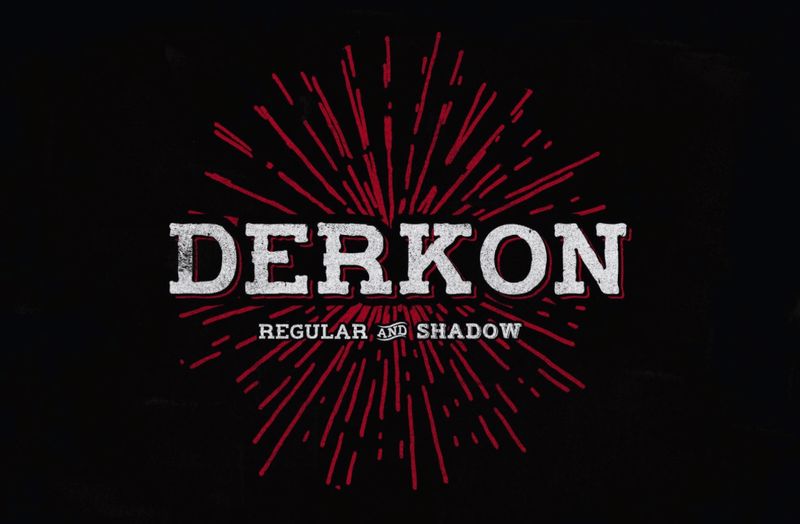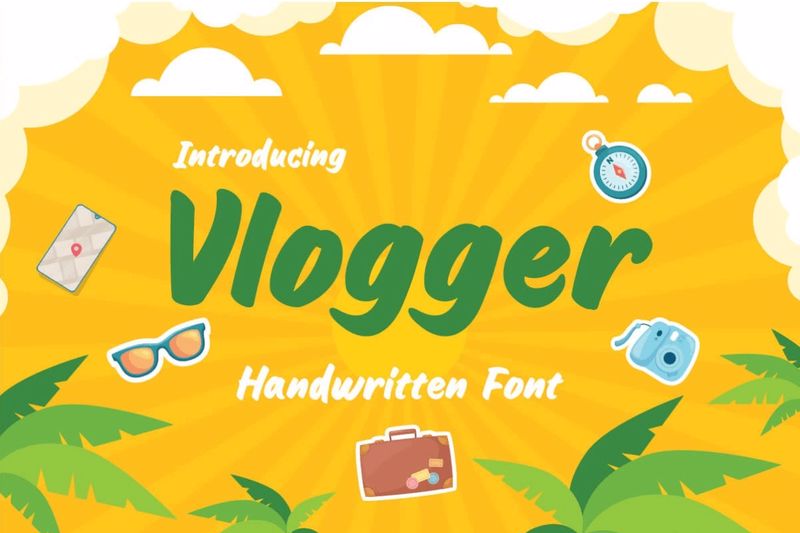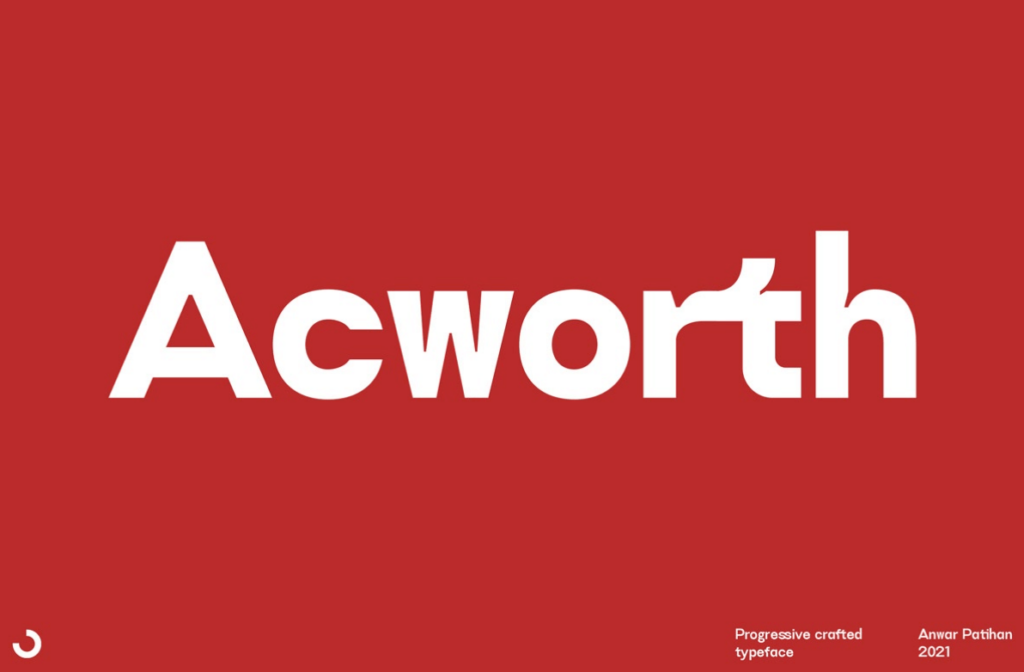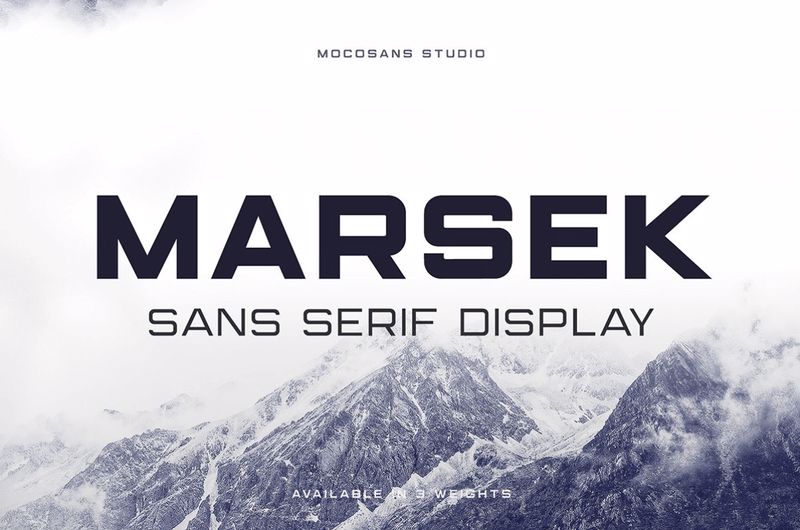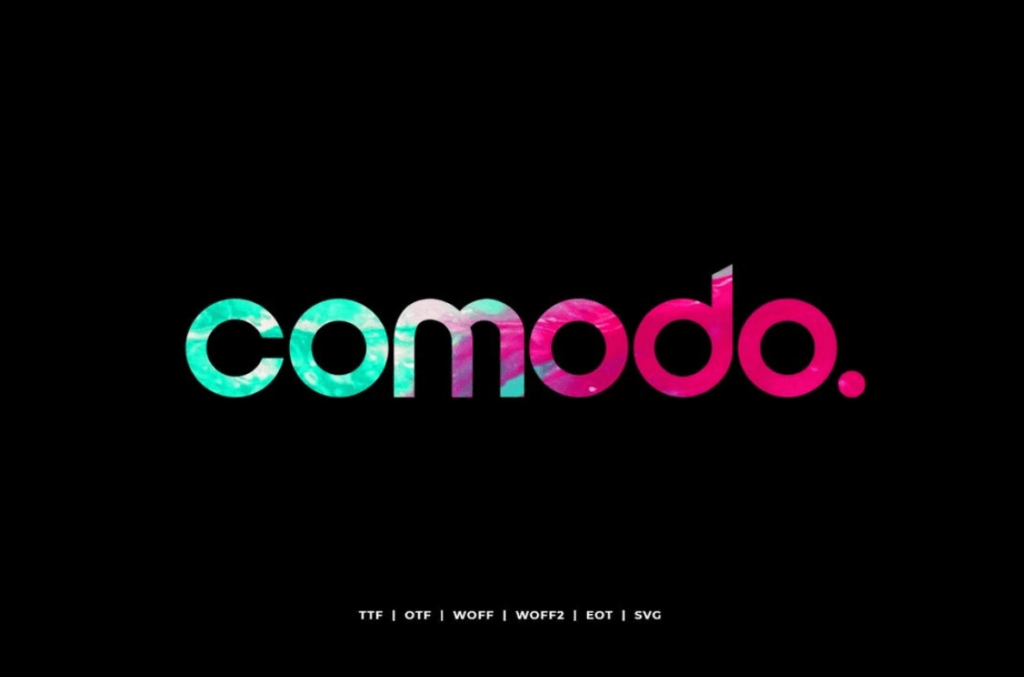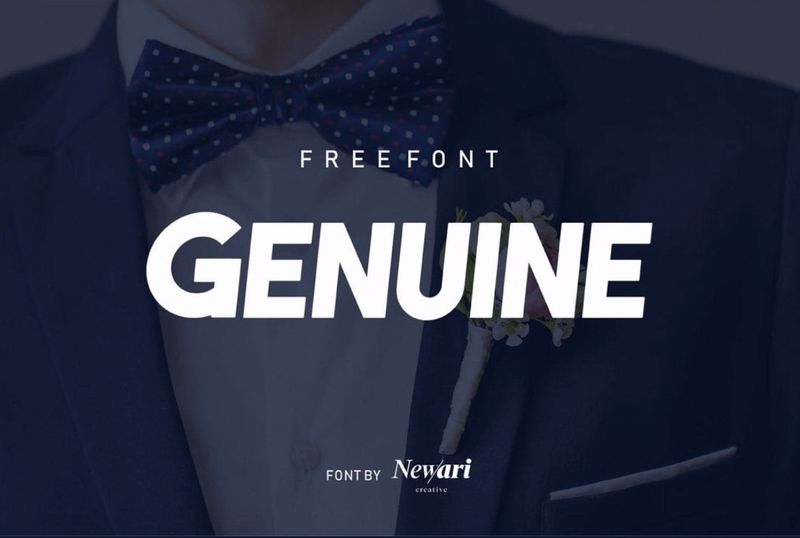
Заголовок веб-сайта — это важнейший элемент дизайна. Он должен цеплять взгляд и пробуждать у пользователей различные эмоции. Если ваш заголовок будет ярким и цепляющим, пользователь задержится на сайте, а ваши конверсии возрастут.
В 1-ой части нашей статьи мы поделились с вами некоторыми советами по выбору шрифтов для заголовков, которые вы уже смело можете применять при разработке своих дизайн-проектов.
Вам не нужно тратить много времени на поиск идеального шифта, потому что в этой части нашей статьи мы продолжим делиться с вами лучшими шрифтами для различных дизайн-проектов.
Derkon — это шрифт для заголовков, который содержит два полных набора заглавных букв и 18 глифов. Шрифт выглядит очень смело и необычно, чем несомненно привлечет внимание вашей аудитории.
Vlogger — это забавный шрифт, который поможет выделить ваш заголовок среди скучной и однообразной массы. Это отличный выбор для различных YouTube-проектов, а также веб-сайтов с игровой, детской и туристической тематикой.
Gemosh — это креативный и уникальный шрифт для заголовков. Этот шрифт универсален, поэтому он идеально подойдет как для официально-деловых сайтов, так и для более расслабленных. Шрифт выглядит очень эффектно и помогает создать винтажную атмосферу.
Acworth — это чистый, современный и профессиональный шрифт, который идеально подходит для деловых заголовков. в 2021 году этот шрифт выглядит очень минималистично и актуально.
Marsek — это элегантный экранный шрифт, который отлично подойдет для веб-заголовков, абзацев и других текстовых элементов на вашем сайте.
Comodo — это современный шрифт, который хорошо сочетается с различными типами контента. Он будет хорошо смотреться как на веб-сайте, так и в публикациях в социальных сетях. Его округлые буквы выглядят очень эффектно и немного футуристично.
Genuine — это современный шрифт, который можно использовать для создания заголовков как для печатных, так и для цифровых изображений, а также для заголовков веб-сайтов. Буквы шрифта имеют небольшой наклон-курсив, что придает ему уникальность.